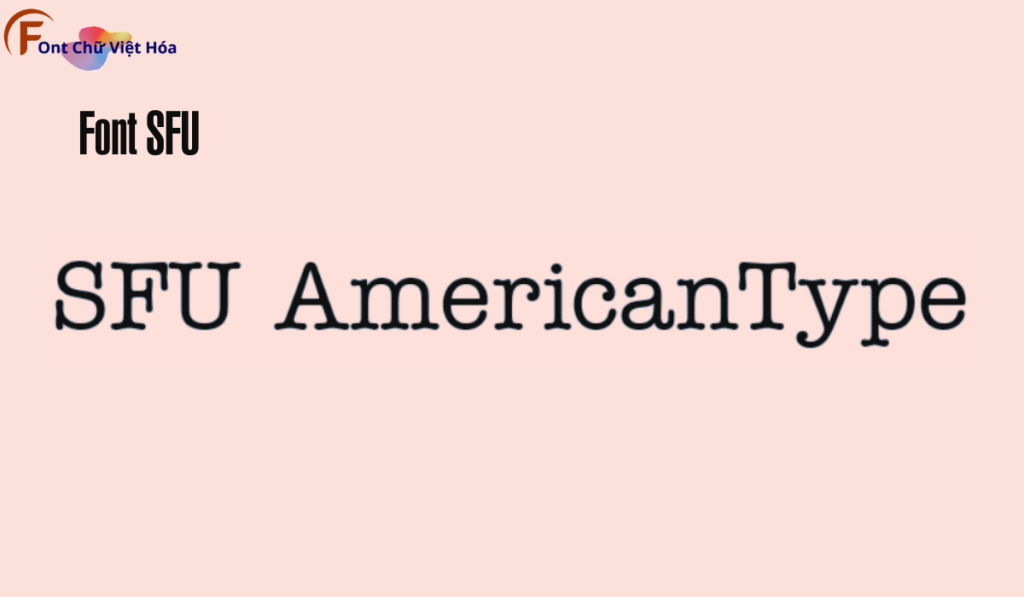
Font SFU American Type Việt Hóa
Bộ Font: SFU
Kiểu chữ: Có chân
Font SFU American Type Việt Hóa, thuộc bộ font SFU, mang phong cách serif cổ điển với các đường nét mạnh mẽ và cá tính. Font này được thiết kế nhằm mục tiêu tạo ra sự rõ ràng và dễ đọc, đặc biệt phù hợp cho các thiết kế như poster, logo, và tiêu đề. Đặc điểm hình dạng của SFU American Type là các đường nét đậm và tỷ lệ chữ cân đối, giúp tạo ấn tượng thị giác mạnh mẽ và sự rõ ràng trong từng chi tiết. Font này cũng đã được Việt hóa, mang đến sự linh hoạt và tiện dụng cho các dự án thiết kế bằng tiếng Việt, giúp người dùng dễ dàng tiếp cận và sử dụng.